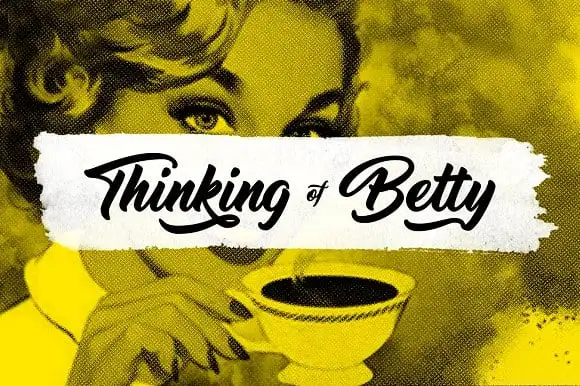
Thinking Of Betty Font – Download Grátis
A Thinking of Betty é uma fonte cíntica bold que oferece uma escrita elegante e vibrante para adicionar um toque único a qualquer projeto. Intuitivamente projetada para designers e amantes da cultura, esta fonte é perfeita para títulos de página ou pequenos detalhes como cabeçalhos, gráficos, listas de texto, ou até mesmo nomes de empresas. O uso do full commercial version lhe dá a opção de experimentar tanto a versão completa quanto uma versão levemente menos robusta que mantém o estilo vibrante da fonte, aliado com um conjunto adicional de alternativas de caracteres e ligaturas contextuais. Estas características extra permitem ao designer explorar ainda mais as possibilidades criativas desta fonte. Para designers dedicados a criar conteúdo visual envolvente para uma variedade de aplicativos, esta fonte Thinking of Betty é uma excelente escolha.
Designer: StereoType